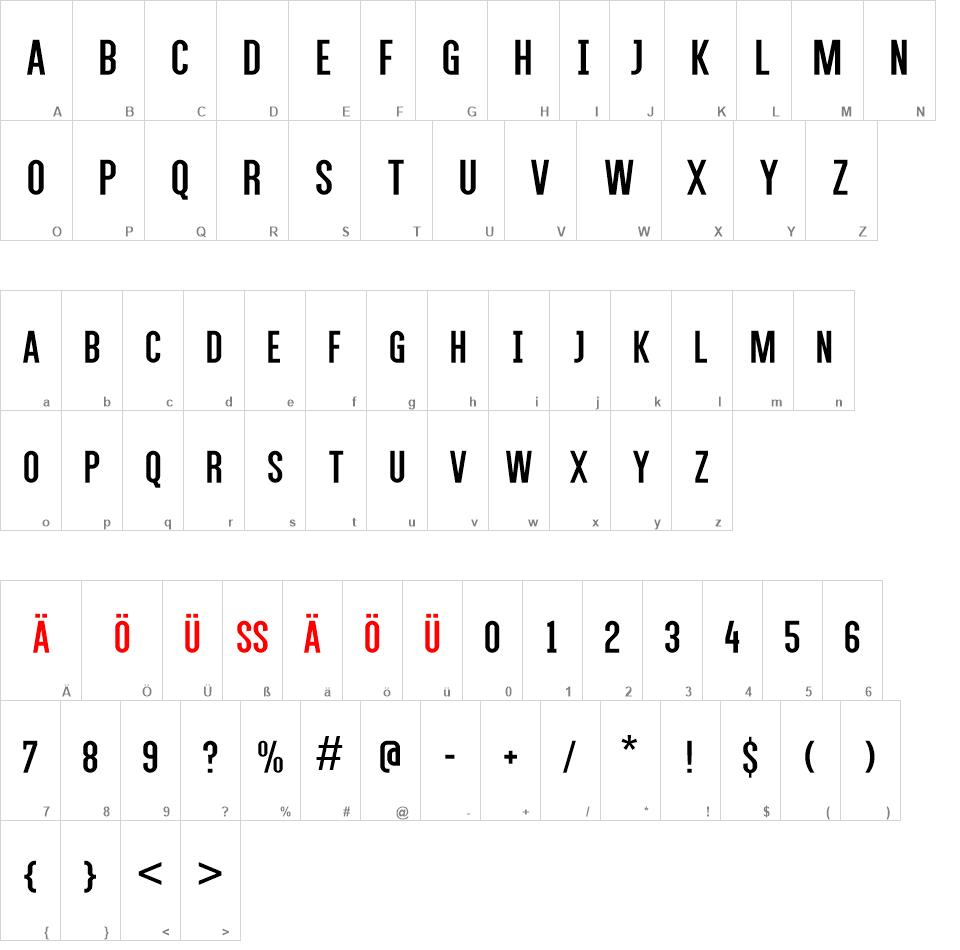
Alégre Sans
Alegre Sans ist eine frei verkürzte serifenlose Schrift, die von GrandChaos9000 entworfen wurde.
UPDATE LOG:
Version 1.2.6 - 1. August 2014
- Entfernte Magzetician kleines Alphabet
- Entfernt QR-Code wegen schlechter Wegbeschreibung
Version 1.2.5-1 - 4. Juli 2014
- Hinzugefügt Symbole für Tonaufnahme Copyright, Copyleft, Copyright-frei und Creative Commons
- QR-Code hinzugefügt
- Geschützter Raum wurde entfernt
Version 1.2.5 - 29. Juni 2014
- Magzetician Alphabet hinzugefügt
- Rubel Währungszeichen hinzugefügt
Version 1.2.0-2 - 18. Juni 2014
- Hinzugefügte und nicht zusammengefügte zusammengesetzte Glyphen
- Schriftart optimiert
- L mit Hub entfernt
Version 1.2.0-1 - 16. Juni 2014
- Kleinere Logo-Korrektur
Version 1.2.0 - 16. Juni 2014
- Griechisch, kyrillisches Alphabet und mehr hinzugefügt
- Hinzugefügt neues Logo und Mags (Magzetician) Währungszeichen
- Hauptschrift neu gestaltet
Version 1.1.0 - 20. März 2012
- Aktualisierte Version
Version 1.0.0 - 16. Juli 2011
- Erste öffentliche Veröffentlichung